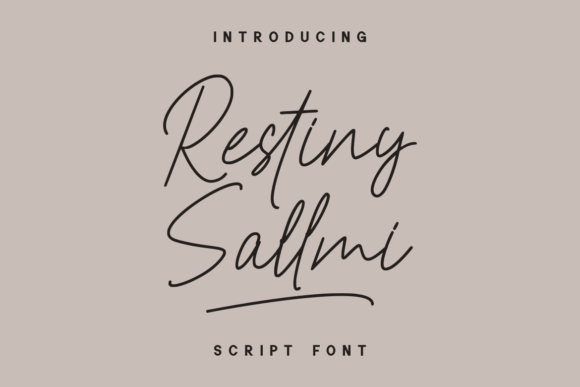
Restiny Sallmi
Znalezienie odpowiednich elementów projektu może być wyzwaniem, ale Restiny Sallmi oferuje wyjątkową kolekcję, która natychmiast ulepszy Twoją pracę.
Precyzyjnie wykonany, Restiny Sallmi zapewnia czyste wektory, płynną typografię i licencję komercyjną dla Twojego spokoju.
Niezależnie od tego, czy tworzysz produkty POD (druk na żądanie), zaproszenia ślubne czy grafiki do mediów społecznościowych, Restiny Sallmi będzie idealnym wyborem.